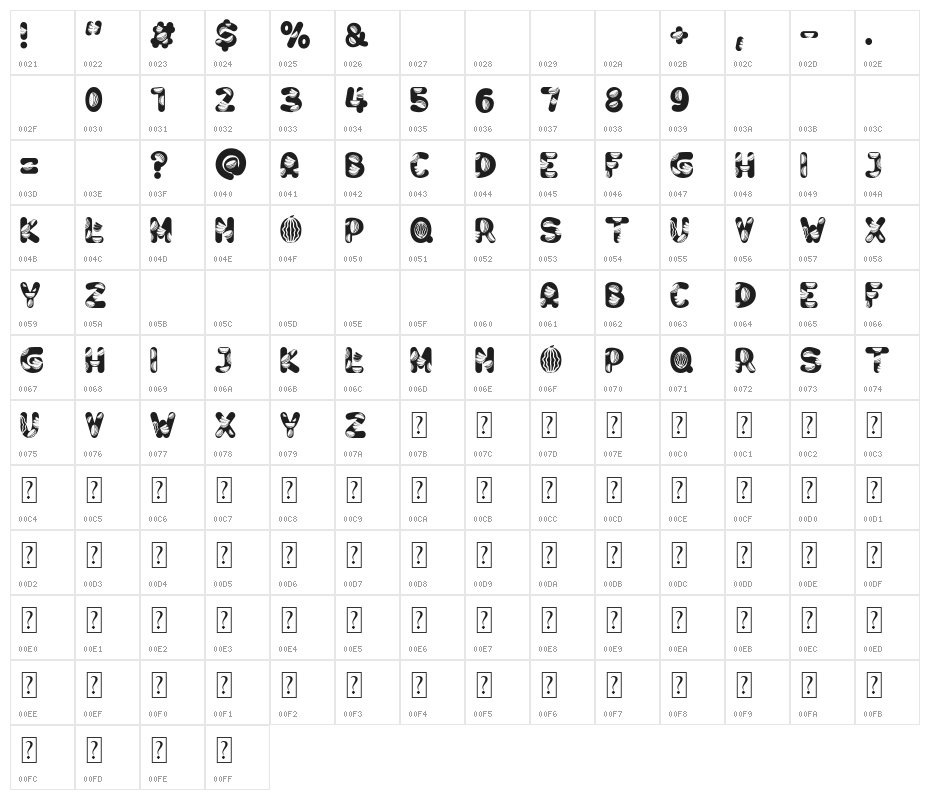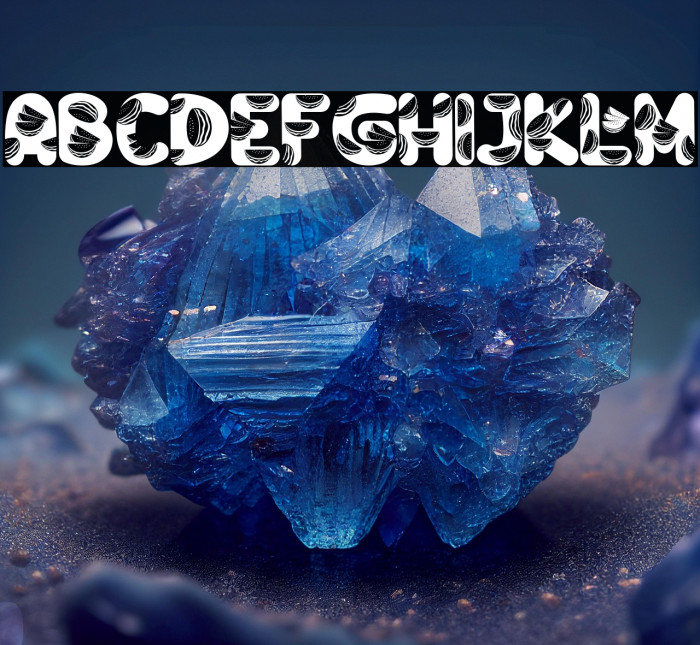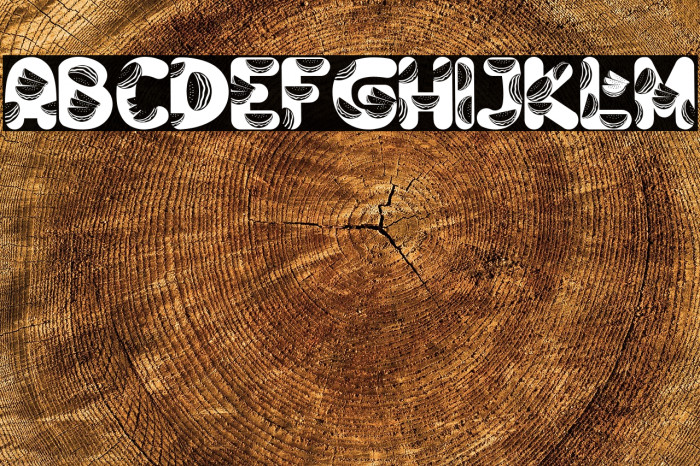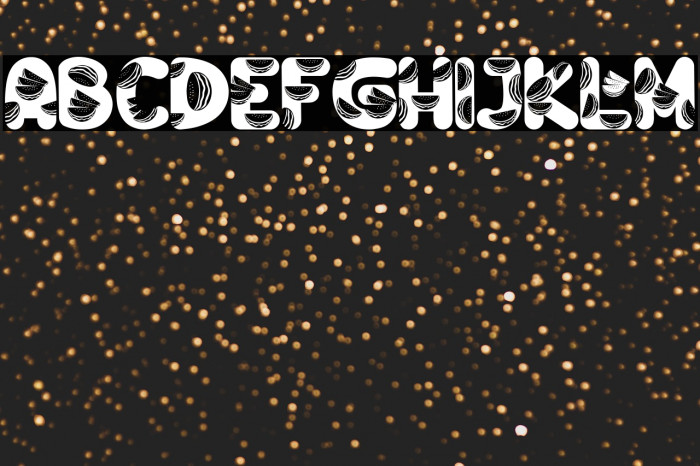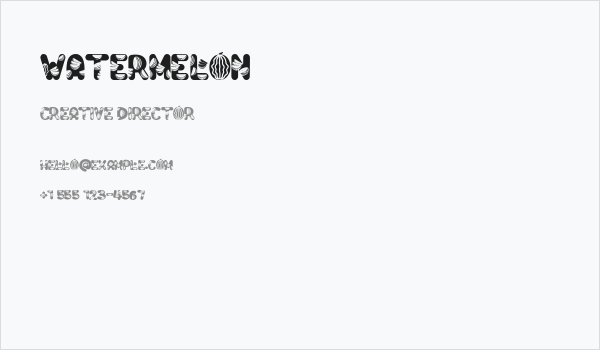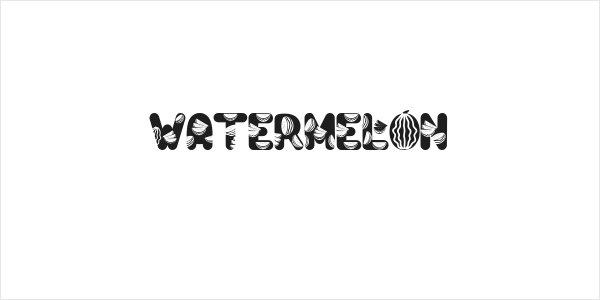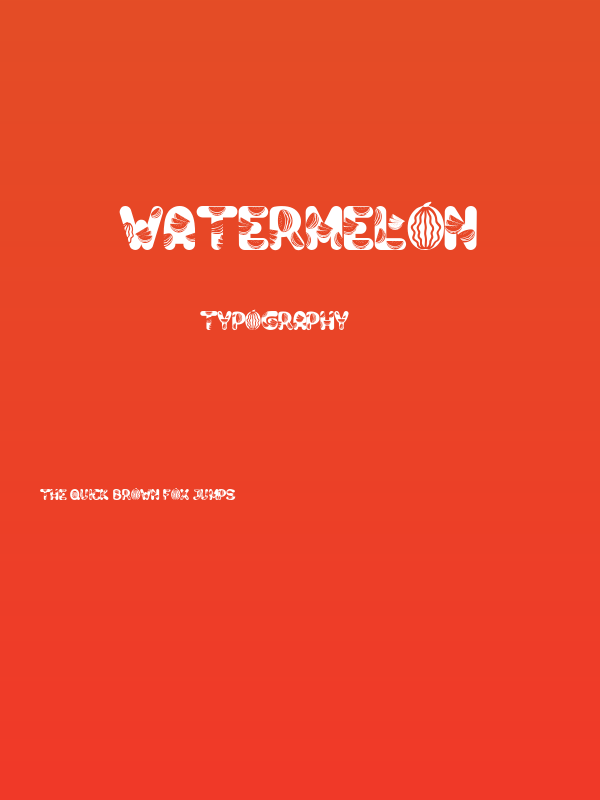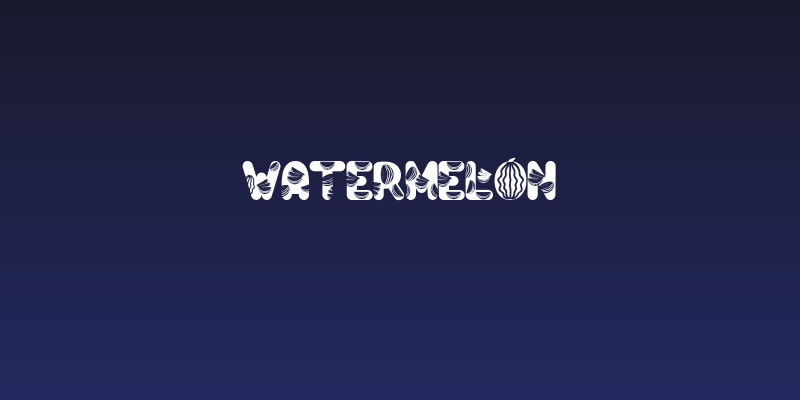
Watermelon Font
| Stile generale | Playful and Whimsical |
| Progetti proposti | Ideal for summer-themed posters, children's book covers, playful branding, and party invitations. |